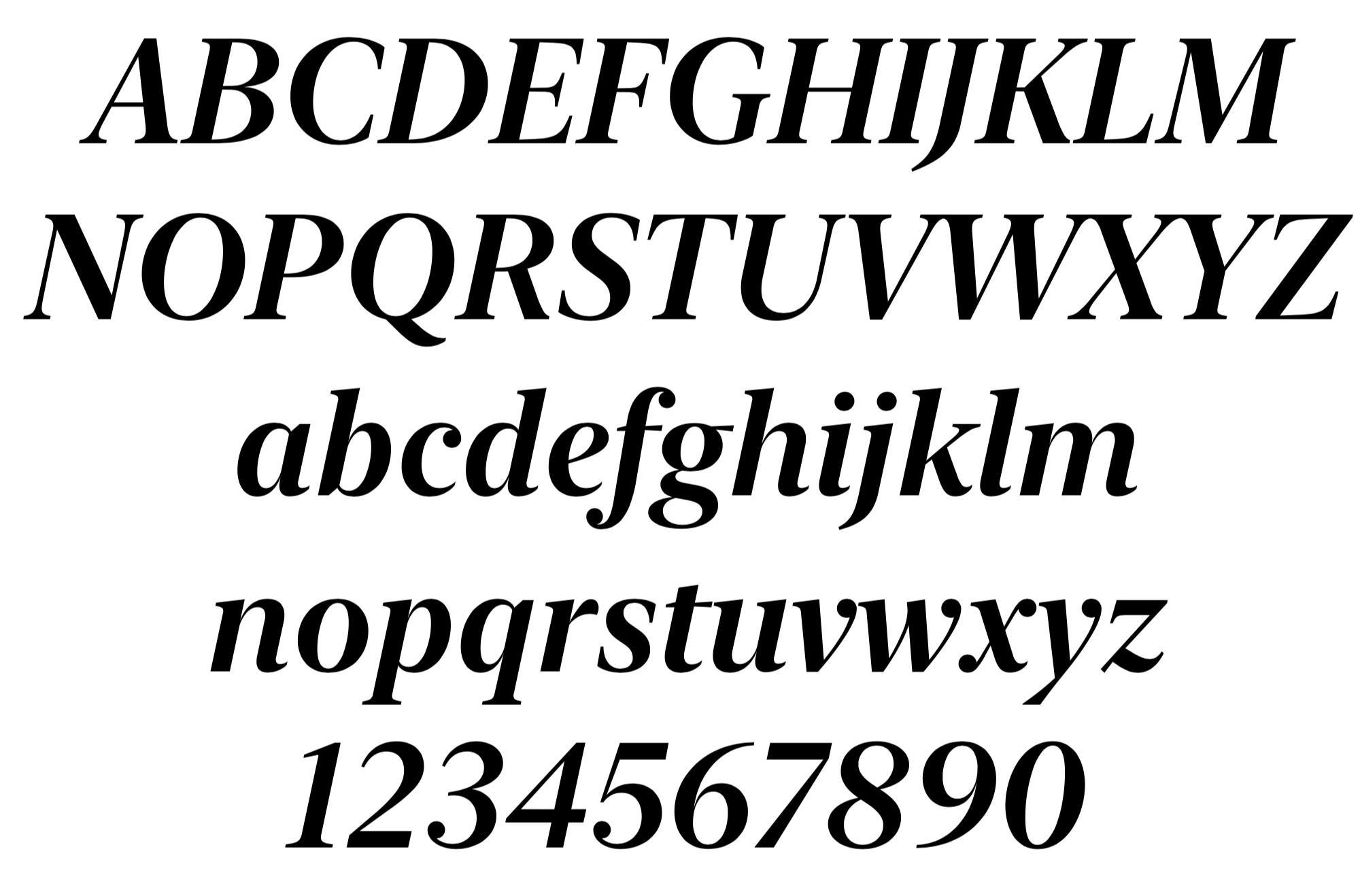
- Antiqua humanistisch
Die Schriftsippe New York ergänzt Apple serifenlose Schriftsippe San Francisco um eine zugehörige Serifenversion. Ursprünglich war das Design nur in der Anwendung Apple Books als »SF Serif« im Einsatz. Seit 2019 steht die Schriftsippe als New York für Apple-Entwickler zum kostenlosen Download bereit. Die Lizenz beschränkt den Einsatz aber auf Anwendungen für Apple-Systeme und die Erstellung von Entwürfe für erstere.
Die erste Veröffentlichung verfügt bereits über 48 Schnitte. Sechs Strichstärken mit Kursiven sind in vier optischen Größen verfügbar. Zum Zeichenumfang gehört eine erweiterte lateinische und eine kyrillische Belegung.
Der Name New York verweist auch auf eine von Apple bereits in den 1980er-Jahren als Teil der bitmap-basierten Systemfonts verwendete Schrift.